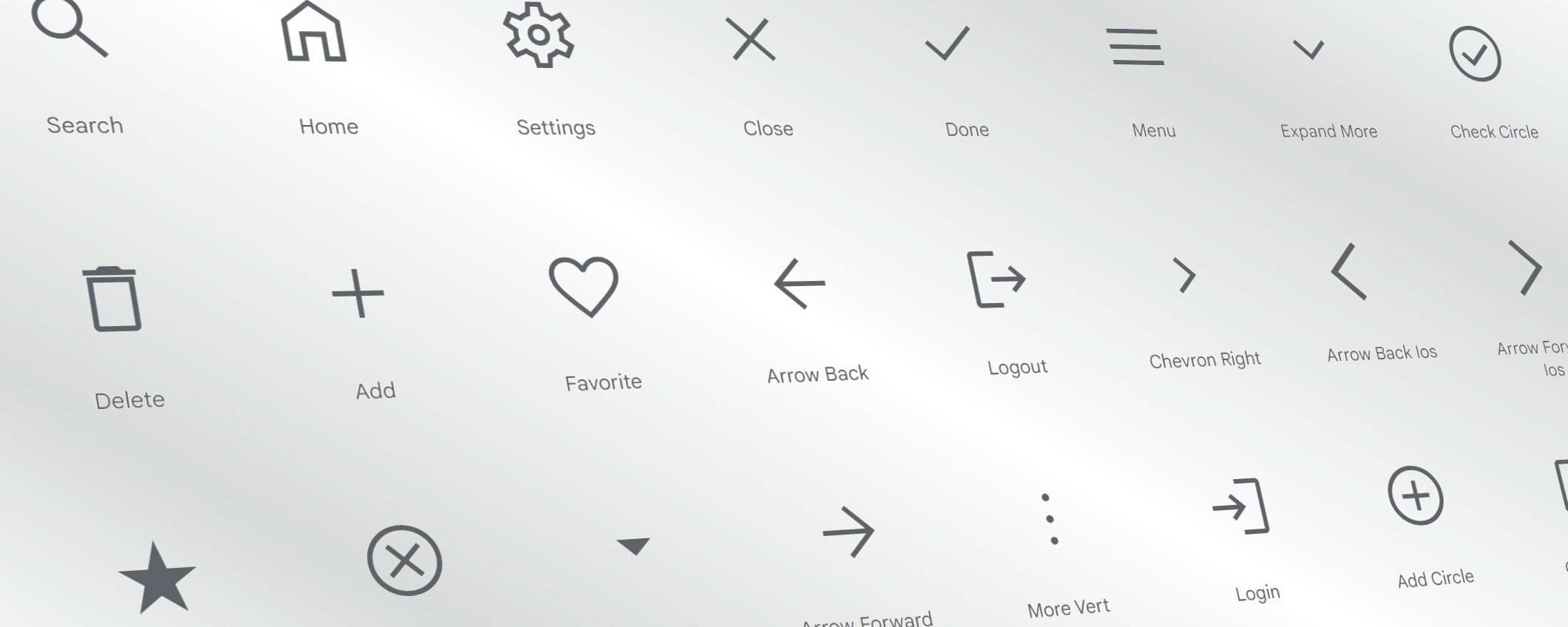
Material Symbols è una collezione da 2500 segni grafici che entrano a far parte dei Google Font a libera disposizione degli sviluppatori.
Google ha aggiunto una nuova famiglia ai propri Google Fonts: si tratta dei Material Symbols, una collezione che potrà avere un importante impatto in virtù della sua trasversale utilità. Non si tratta infatti della classica famiglia di font: in questo caso è una collezione da 2500 glifi che possono essere utilizzati in moltissime occasioni.
Material Symbols
Non soltanto lettere e numeri, insomma: Material Symbols aggiunge un nuovo tipo di utilità ai Google Fonts, peraltro con un’altissima versatilità per meglio sposare ogni tipo di esigenza stilistica.
• Activities,
• Android,
• Audio & Video,
• Brand,
• Business & Payments,
• Common actions,
• Communication,
• Hardware,
• Home,
• Household,
• Maps,
• Others,
• Photo & Image,
• Privacy & Security,
• Proprietary,
• Social,
• Text Formatting,
• Transportation,
• Travel,
• UI actions
Material Symbols